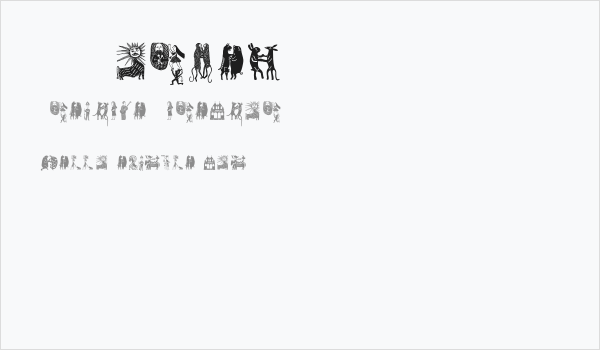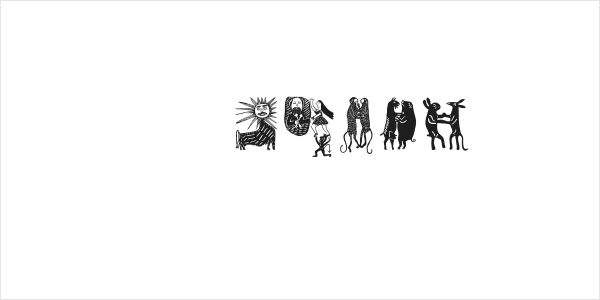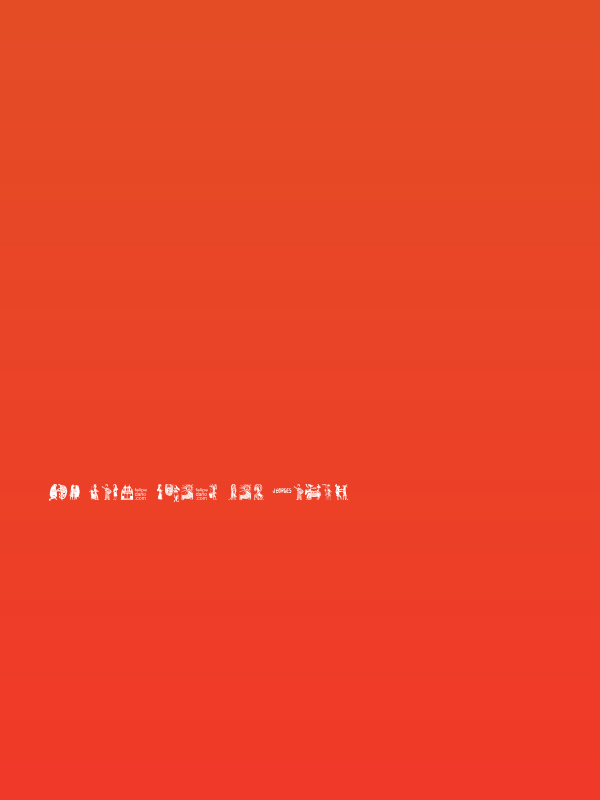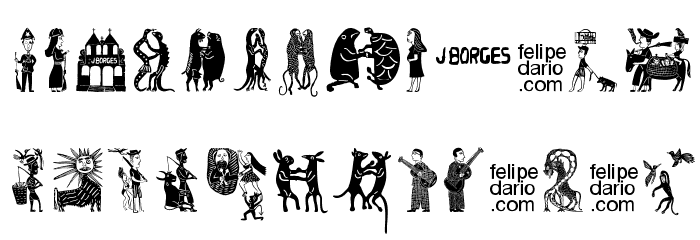
FDJBorges Font
| Estilo geral | Artistic, Folk |
| Caso de uso | Decorative, Artistic projects |
| Projetos propostos | Ideal for artistic projects, posters, book covers, or any creative work that benefits from a unique and illustrative touch. |